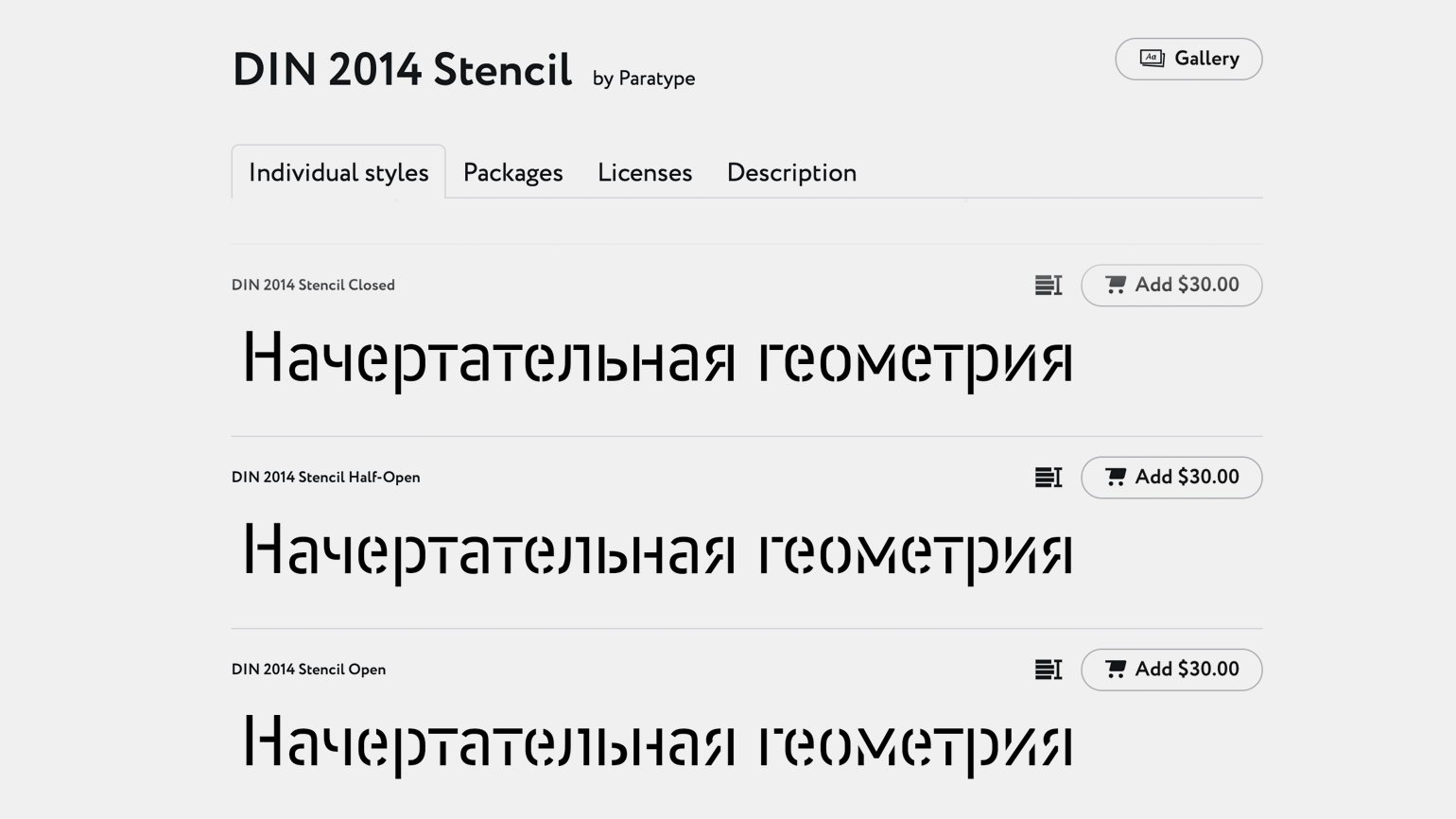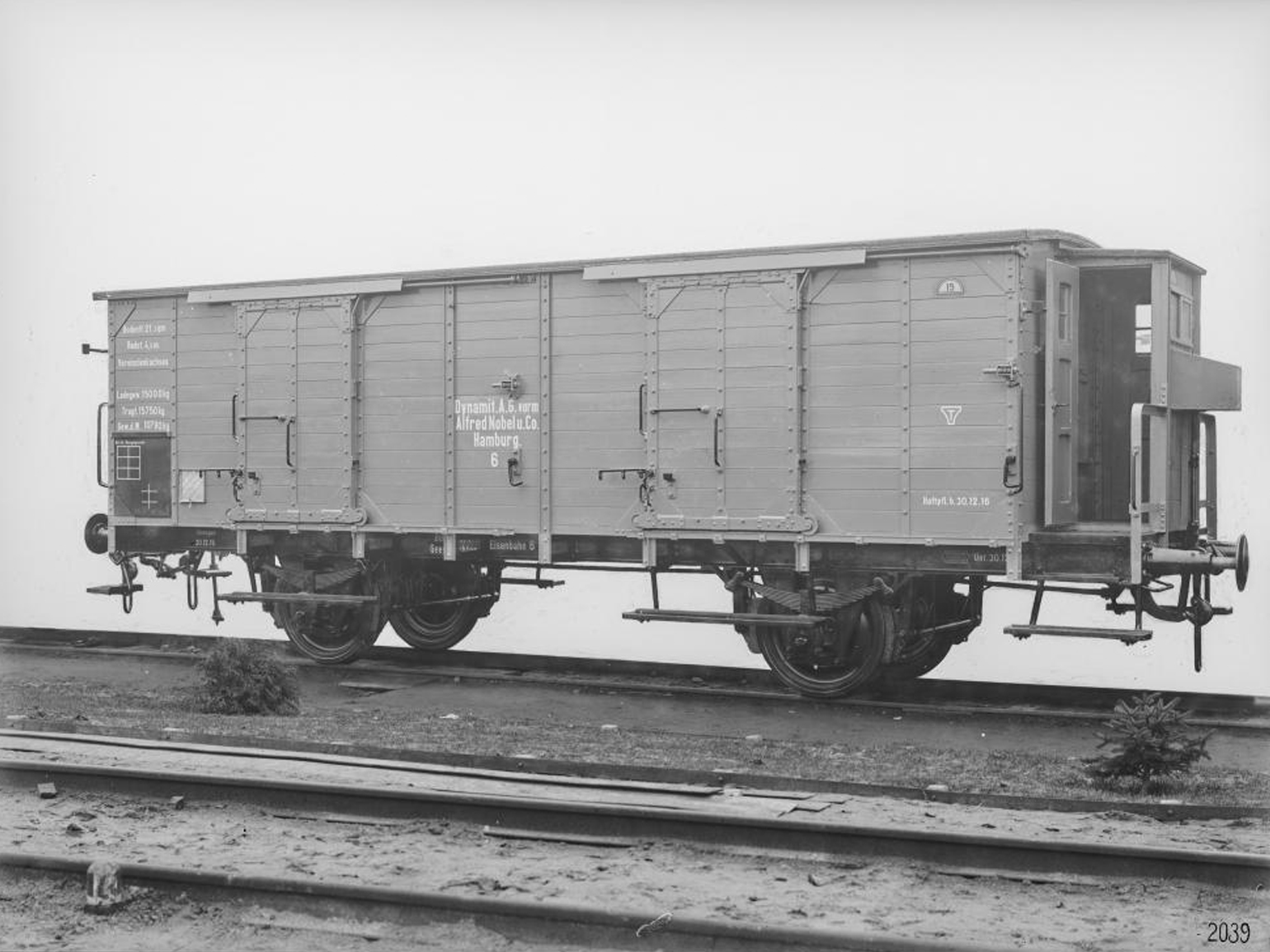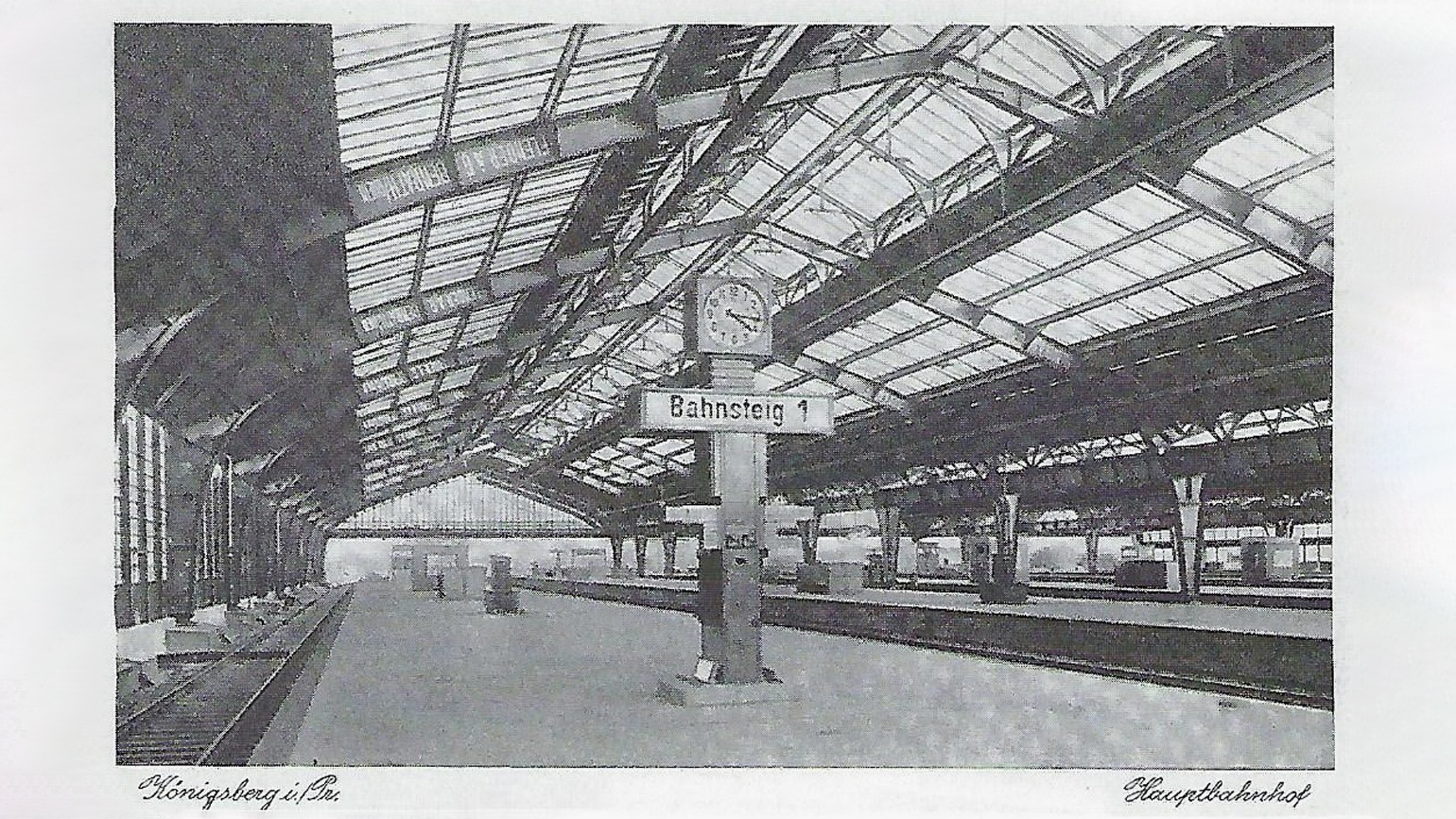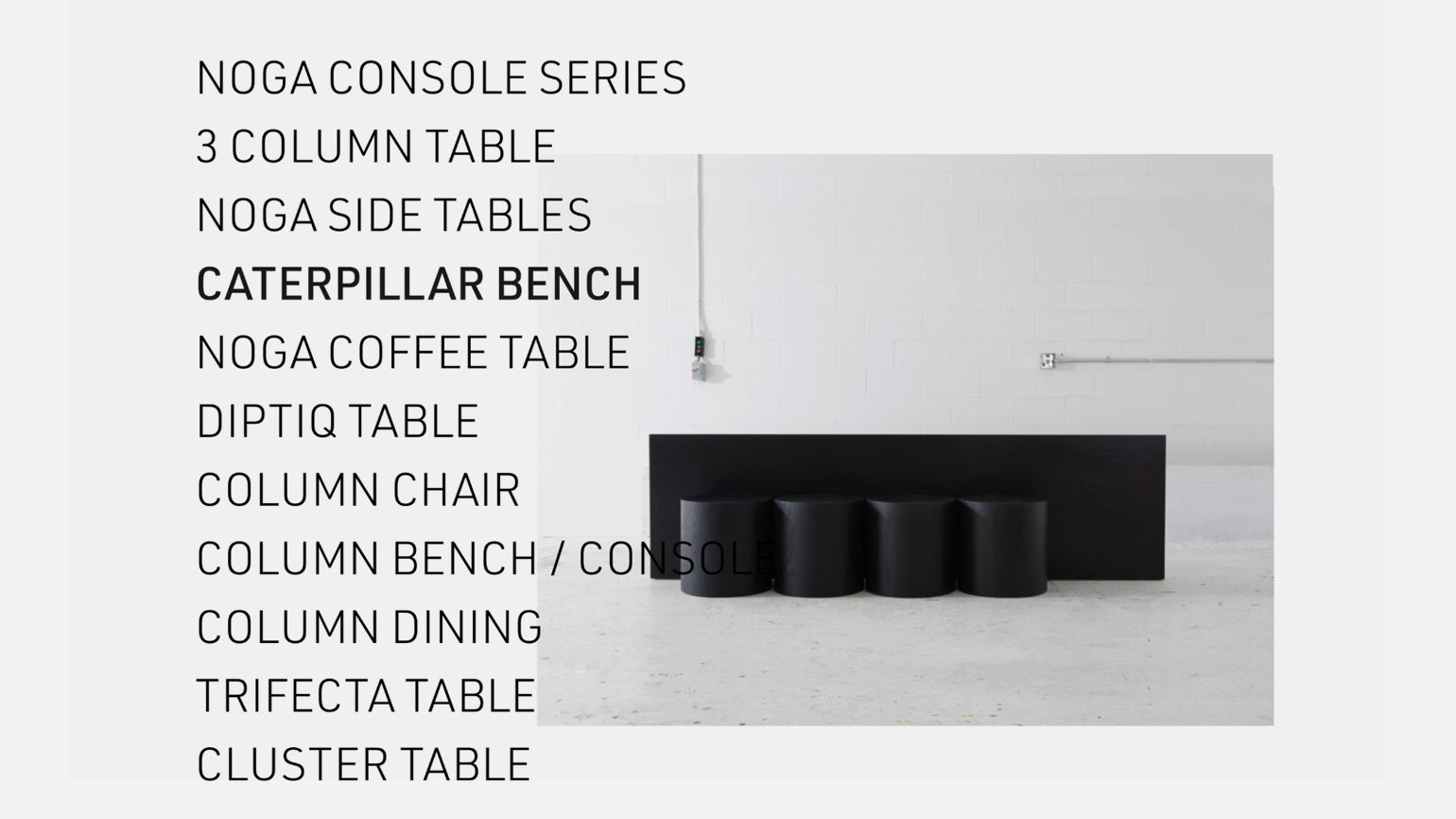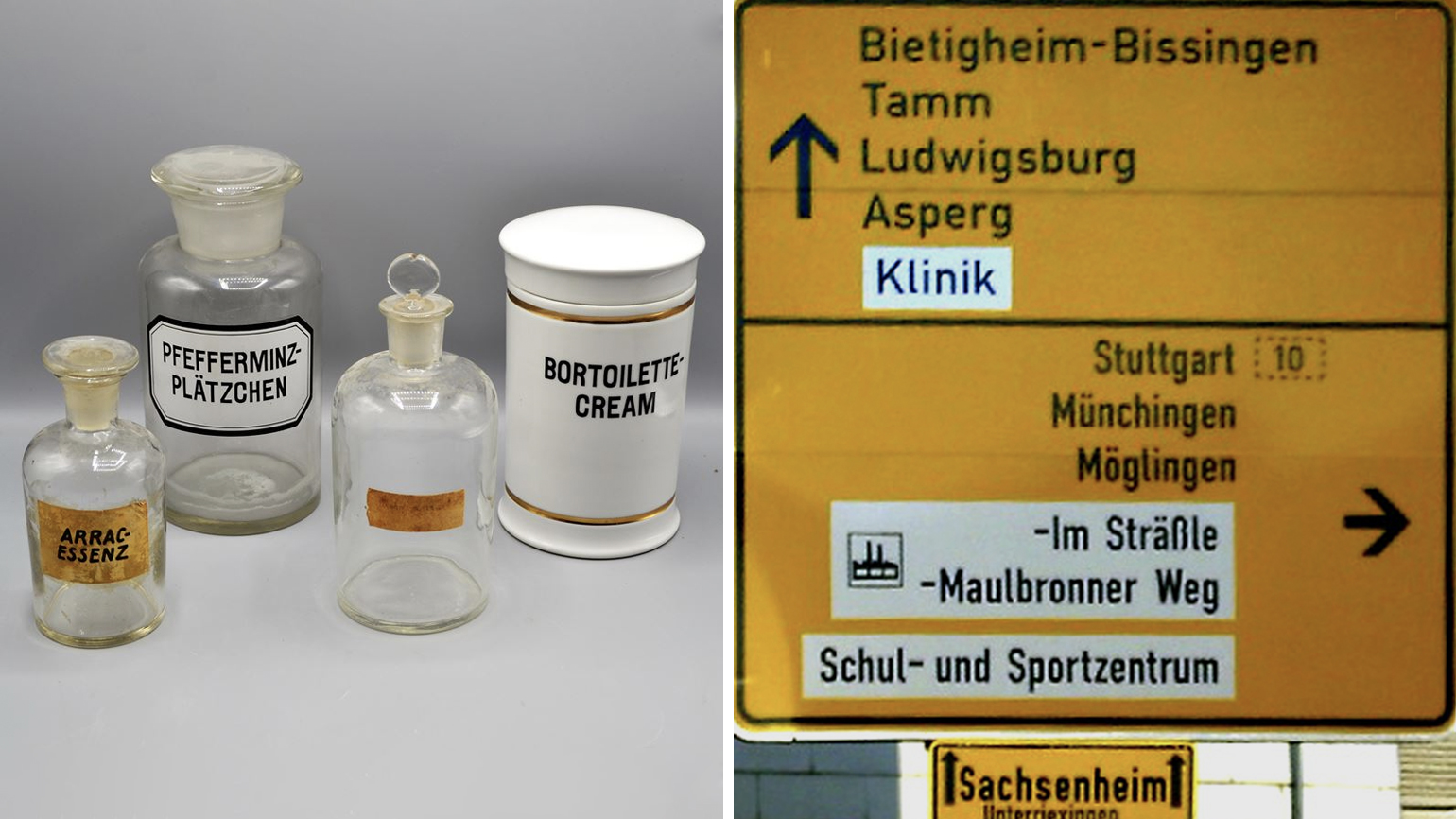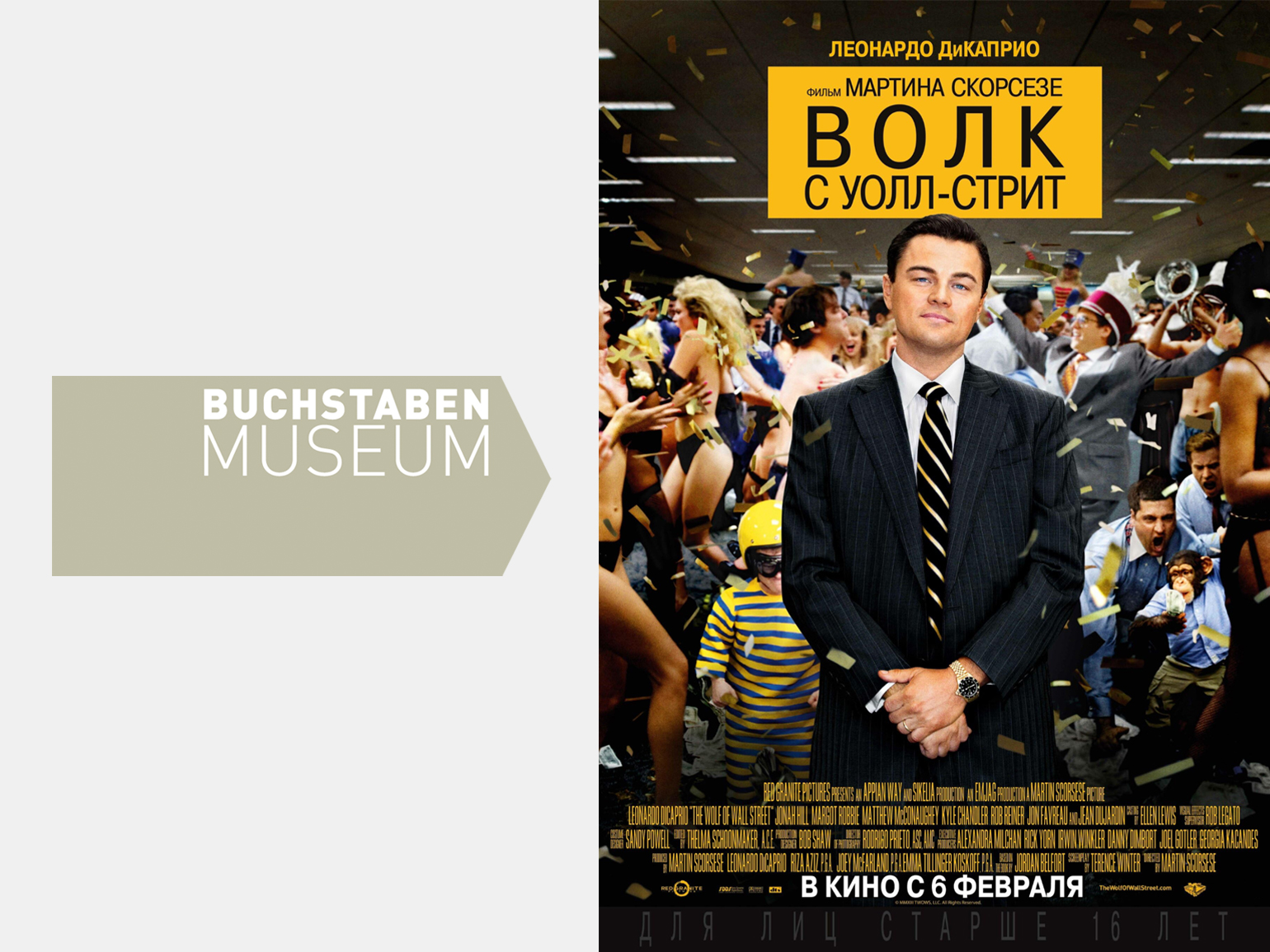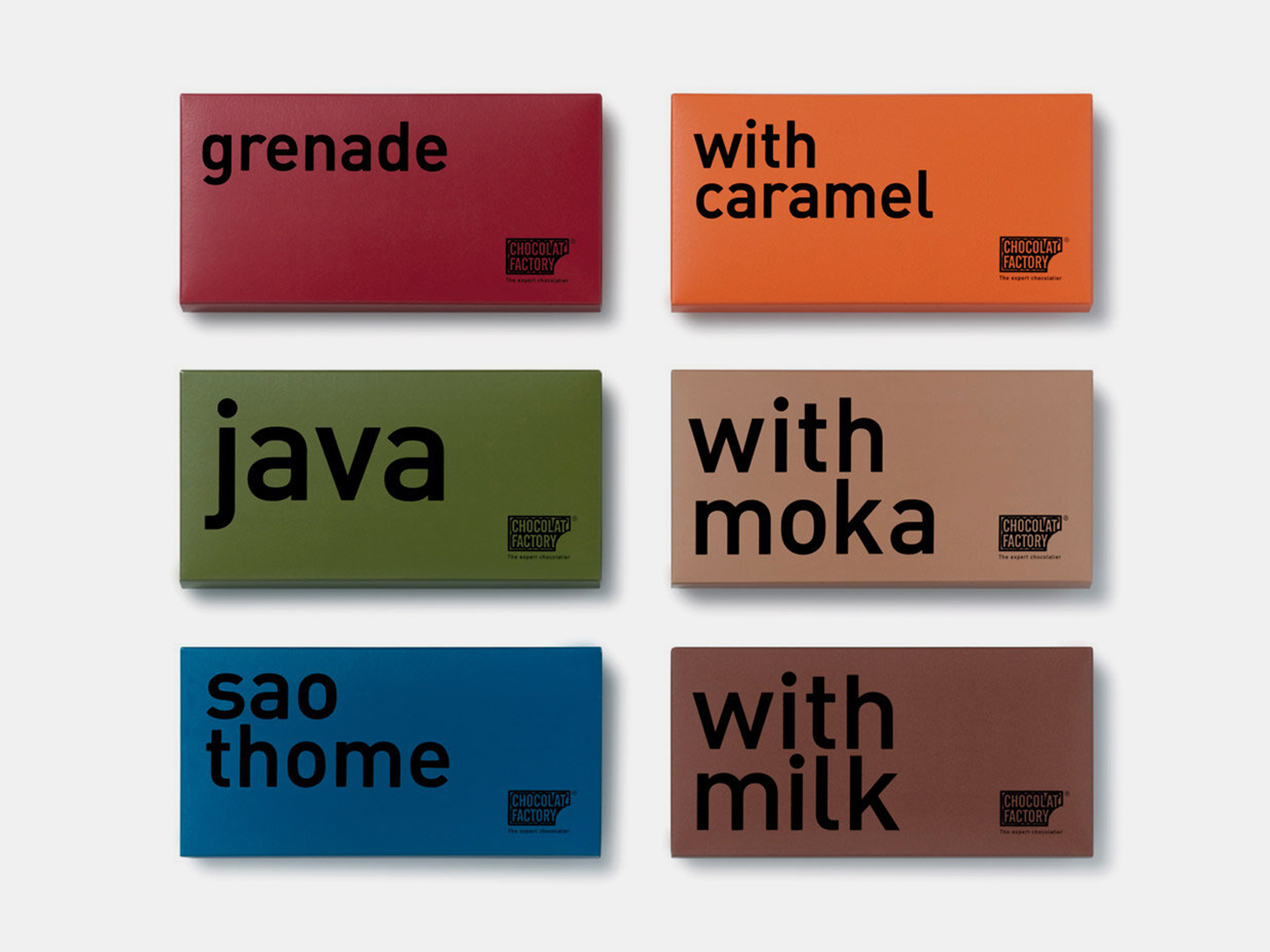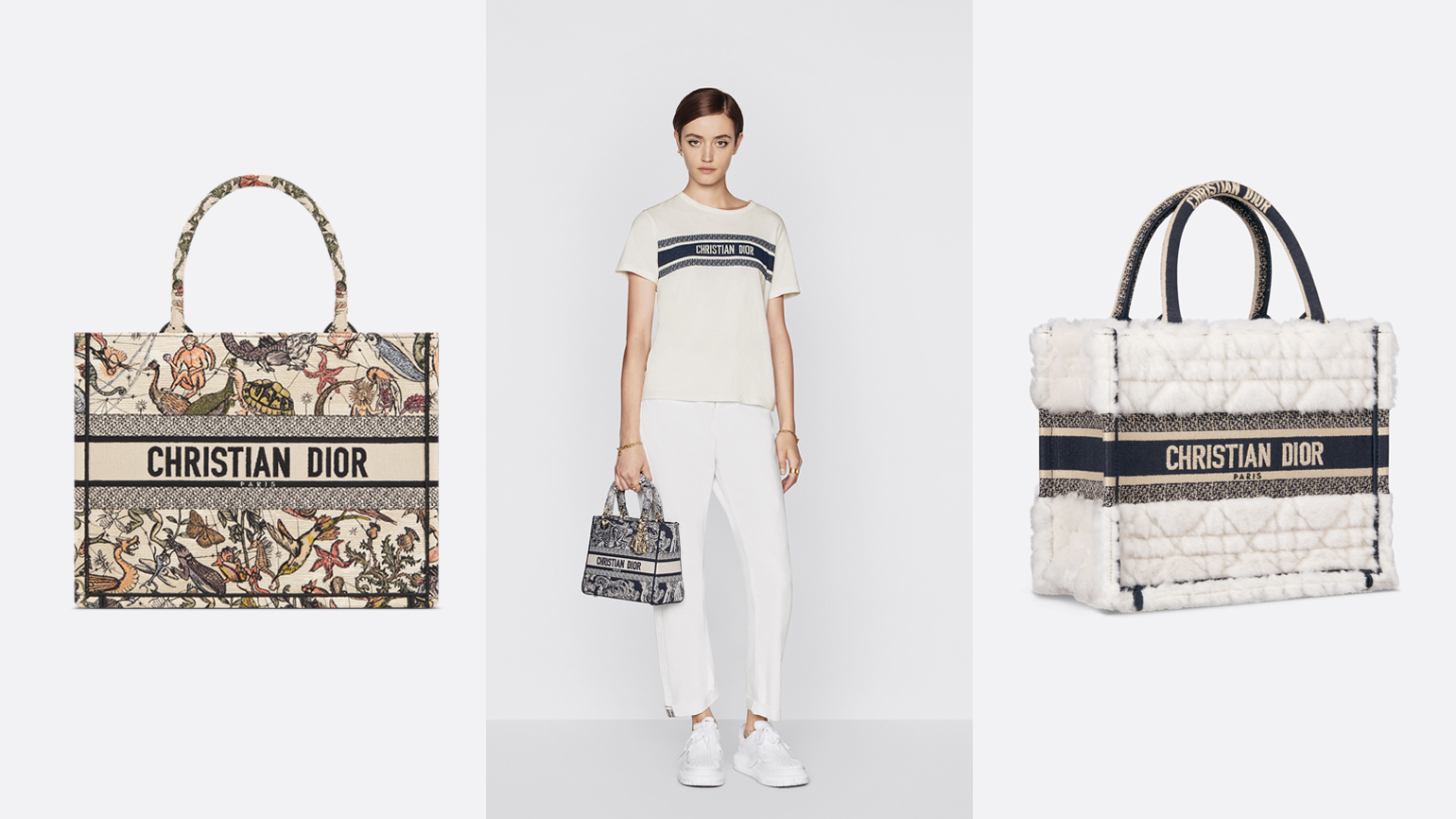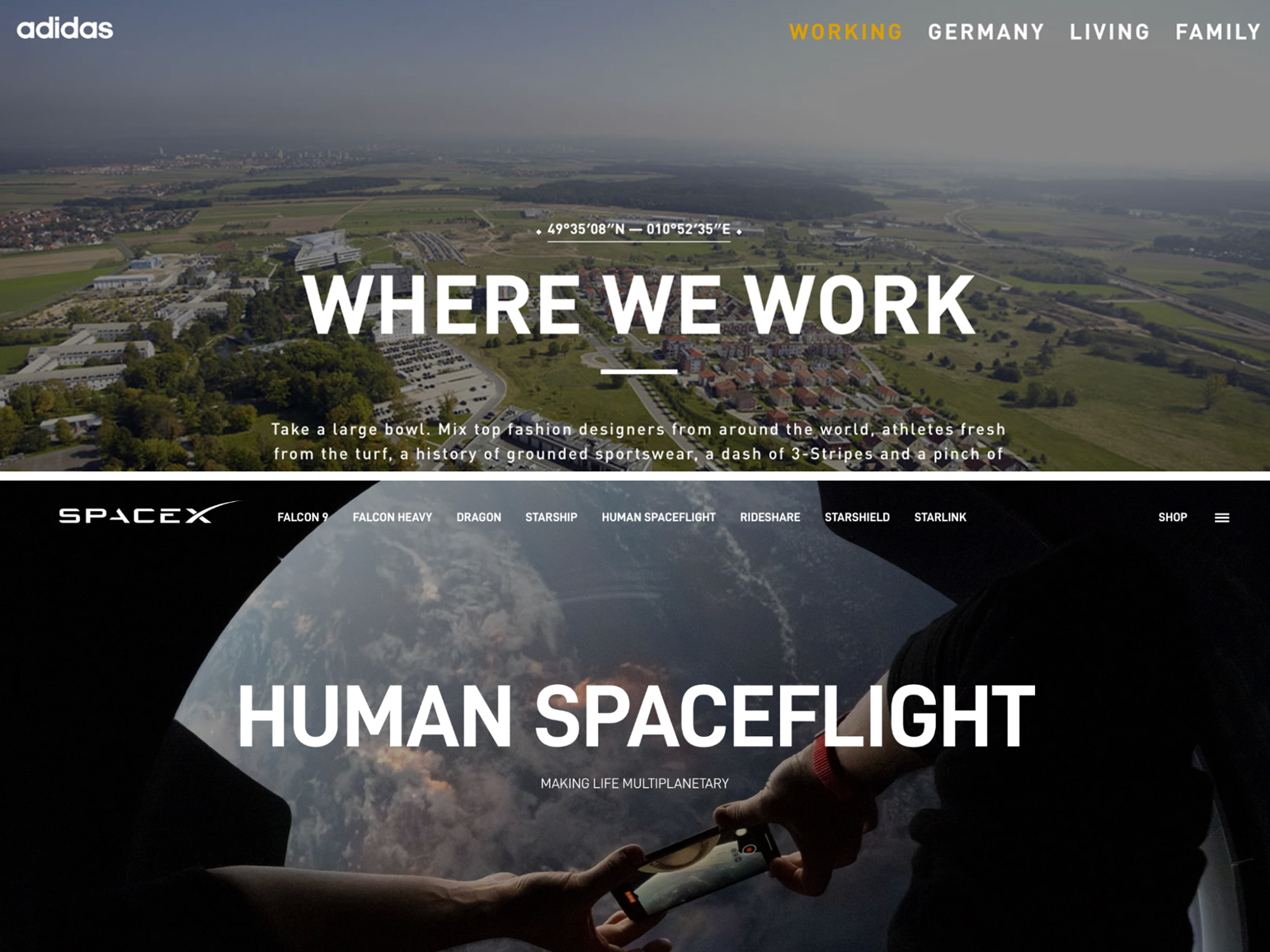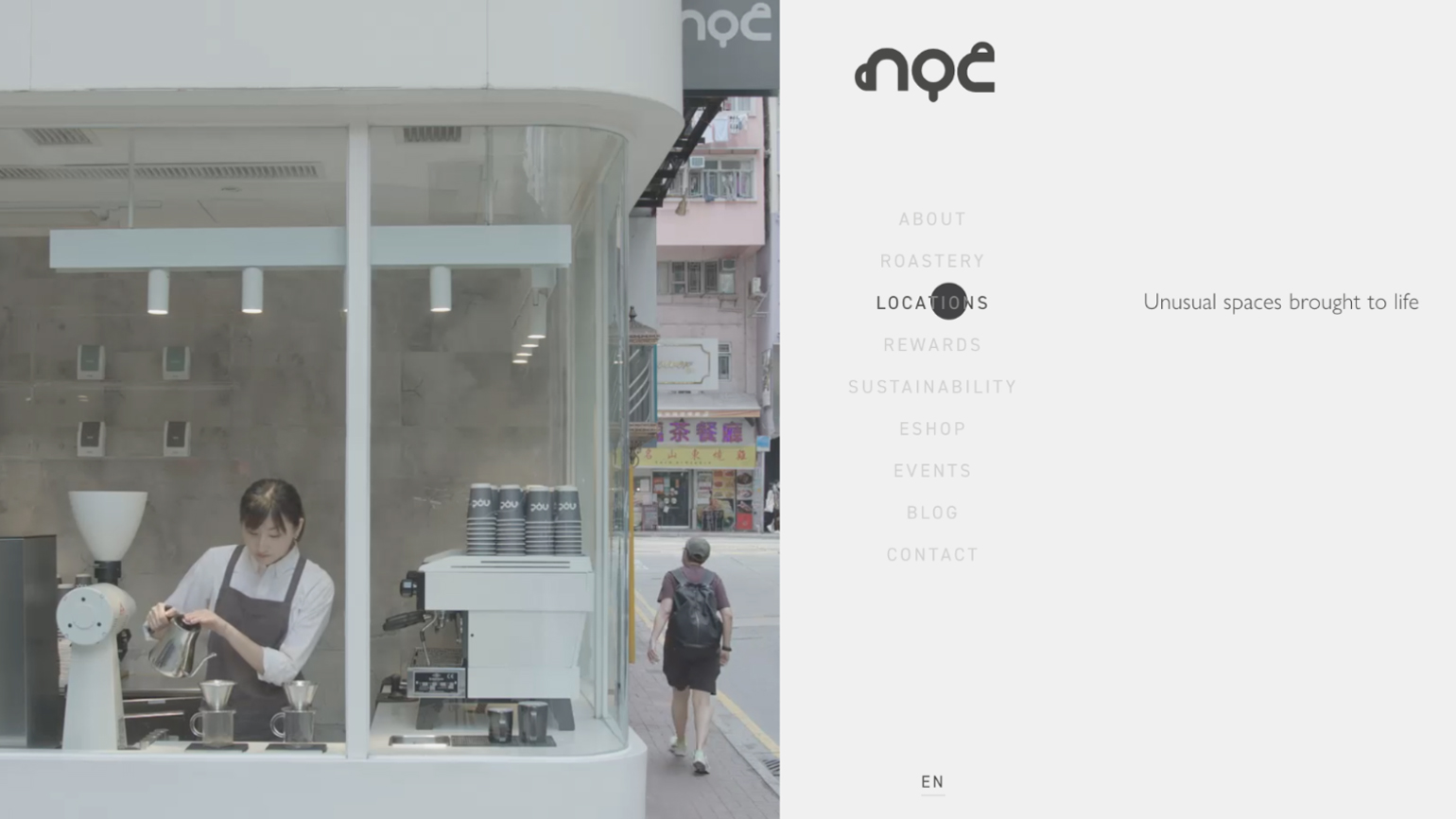
Шрифты DIN: где используют и с чем сочетают
Рассказываем, как появилась популярная шрифтовая графика, и показываем примеры дизайна с разными видами DIN.
DIN: что это за шрифт
В 1995 году нидерландский дизайнер Альберт-Ян Пул выпустил набор шрифтов без засечек с нейтральным, но довольно строгим характером. И хотя это был полностью его собственный дизайн-проект, за графикой стояла долгая история инженерии, технических регламентов и целого государства.
В 1871 году Отто фон Бисмарк провозгласил создание Германской империи: прежде государства не существовало — это были отдельные мелкие монархии и королевские земли. Началось постепенное и долгое объединение страны на всех уровнях — политическом, промышленном, гражданском, и во многих процессах доминировала Пруссия и прусские организации, в том числе эстетически.
Так, в 1920 году произошло объединение разрозненных железнодорожных перевозчиков в единую национальную компанию. Для указателей и обозначений на линиях по всей стране стали использовать чертежи, по которым делали надписи на вагонах Прусских железных дорог.
Надписи на грузовом вагоне Прусской железнодорожной компании, 1915 год
Указатель «Платформа №1» на главном вокзале Кёнигсберга, 1929 год
А ранее, в 1917 году, был основан Немецкий институт стандартизации, Deutsches Institut für Normung — DIN. В 1927 году в организации решили: необходимо создать нормализованный, единый и строгий шрифтовой стандарт для навигации и централизованных коммуникаций.
В 1931 году институт выпустил DIN 1451 — набор документов и регламентов, которые определяли геометрию и графику букв, цифр и прочих знаков в инженерных и технических чертежах. В 1936-м DIN 1451 приняли как стандарт для оформления указателей, информационных табличек, навигации на улицах и в бомбоубежищах.
Чертежи разработали на основе жёсткой расчётной сетки, и каждый знак можно было быстро отрисовать циркулем и линейкой.
Визуально у надписей, начерченных по этому стандарту, была жёсткая структура, и знаки были прекрасно различимы издалека. DIN 1451 со временем распространился шире, чем предполагалось: эту шрифтовую графику с чистыми, визуально простыми линиями букв стали использовать на аптечных этикетках, на вывесках и даже в рекламе. Вероятно, популярен он стал в том числе и потому, что «государственный характер» стандарта придавал текстам уверенный, деловой характер.
Шрифтовое оформление по стандартам DIN 1451 стало визуальным символом Германии. Стандарт 1936 года описывал три формата: Engschrift (зауженный), Mittelschrift («средний», обычной ширины) и Breitschrift (широкий)
В Берлине есть площадь, названная в честь Института по стандартизации
Альберт-Ян Пул скрупулёзно работал над шрифтами, основанными на стандарте DIN 1451, с начала 1990-х. В результате он превратил популярный формат в крупное шрифтовое семейство FF DIN (FF означает, что оно вышло в его студии FontFont). Сейчас в коллекцию входят:
• 14 начертаний FF DIN Condensed — от Thin до Black и соответствующие курсивы.
• 14 начертаний «стандартного» FF DIN — также от Thin до Black и соответствующие курсивы.
Однако FF DIN — не единственный «дин». Есть множество шрифтов этого формата, произведённых в разных студиях: DIN Next от Акиры Кобаяши и Сандры Винтер, DIN 2014 от «Паратайп», PF DIN от Parashute.
— Все версии DIN похожи, но это не копии одного образца: все они пытаются изображать одну и ту же пластическую идею.
Оригинальный стандарт DIN — это не шрифт, а скорее чертёжная инструкция. Её можно отрисовать, но в процессе дизайнеру захочется многое исправить, кое-что осовременить. В любом случае придётся подбирать насыщенность, пропорции, настраивать ритм.
Кстати, у нас сейчас в студии как раз идёт разработка очередного «дина».
Дмитрий Голуб,
основатель шрифтовой студии и школы шрифтового дизайна Bolditalic
Альберт-Ян Пул показывает технические листы с чертежами стандартного немецкого шрифта
Изображение: FontFont by Monotype / Behance
Существуют и альтернативные версии DIN — например, DIN 2014 Stencil.
Дизайн этих шрифтов отсылает к трафаретам, с помощью которых создавали стандартизированные надписи. Эти трафареты существовали и в виде больших металлических листов для нанесения надписей на борта самолётов, и в виде прозрачных карточек с прорезями для черчения на объявлениях.
FF DIN стал одним из самых популярных инструментов дизайна. Он неизменно в топе продаж на сайте My Fonts: в марте 2024 года он на 8-м месте в списке бестселлеров.
В 2011 году FF DIN вошёл в коллекцию прикладного искусства MoMA.
FF DIN в логотипе Музея букв и в киноайдентике